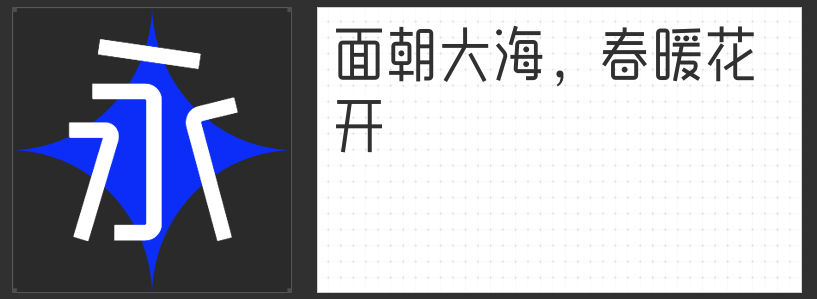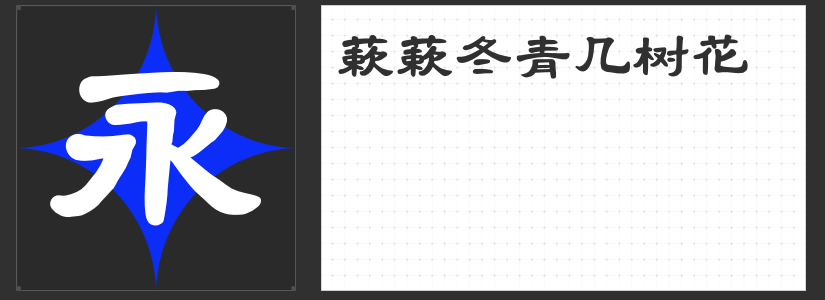
冬至设计美学指南:四款风格字体解锁传统节气新表达
冬至作为兼具自然与人文内涵的节气,其设计需兼顾文化底蕴与视觉温度。以下四款风格迥异的字体,以不同维度诠释冬至的意境,为节气主题设计提供多元灵感。
一、励字勇敢黑简 特黑
这款无衬线字体以粗壮笔划构建视觉骨架,横竖均匀的布局如冬至日影般稳定庄重。撇捺收笔的钝角处理弱化了锋利感,在保持标题醒目度的同时,传递出"冬至阳生春又来"的蓄势能量。其简洁有力的形态适用于节气主题LOGO、导语标题等核心信息传达,与冬至的团圆主题形成刚柔并济的视觉对话。
二、MyFont郑明瑾卡通简
以自然弧线与柔和转角塑造的亲和字形,恰似冬至汤圆般饱满可爱。字体结构中隐含的微笑弧度,为寒冬注入温暖治愈的气质。这款字体通过圆润笔画与适度留白,在保持儿童向设计天性的同时,亦可通过调整字间距营造传统节气的雅致感,适合用于节气文化科普、品牌温情传播等场景。
三、创客贴阳光体
修长字身与全圆角处理的独特组合,赋予文字轻盈跃动的视觉节奏。点笔画的圆形设计如雪粒飘落,转角处的弧度似冰晶折射,在可爱童趣中暗藏冬至物候特征。这款字体通过形态创新平衡传统与现代,既可单独作为装饰元素,亦可与隶书、宋体等传统字体搭配,形成时空交错的节气叙事。
四、创客贴新隶书
燕尾蚕头与波磔挑势的经典隶书结构,为冬至设计注入历史沉淀的厚重感。横画蚕头收笔的弧度暗合"冬至一阳生"的哲学意象,竖画收尾的波挑似寒梅枝干,在传统韵律中传递节气智慧。此款字体适合用于节气诗词呈现、文化展览主视觉等需要文化深度的场景,与现代设计元素结合可碰撞出独特的时空美感。
四款字体从力量美学到童趣表达,从现代创新到古韵传承,为冬至设计提供了多维度的美学解决方案。设计师可根据具体场景需求,通过字体组合或单独运用,在节气视觉叙事中构建传统与现代的对话空间。